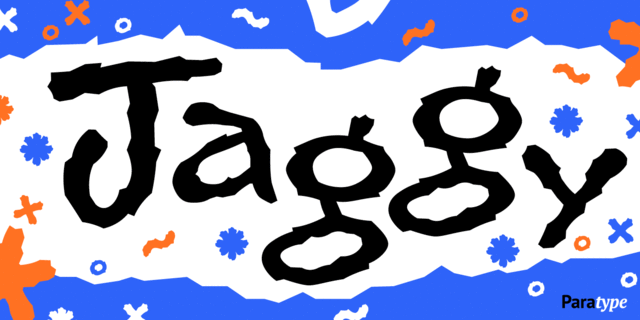
Рукописный шрифт разработан для компании ПараТайп в 2006 году (дизайнер Изабелла Чаева) на основе неформального рукописного почерка. Его буквы имеют рваный зазубренный контур, что в мелких кеглях дает эффект письма фломастером по грубой неровной бумаге. Шрифт предназначен для применения в рекламе и акциденции.